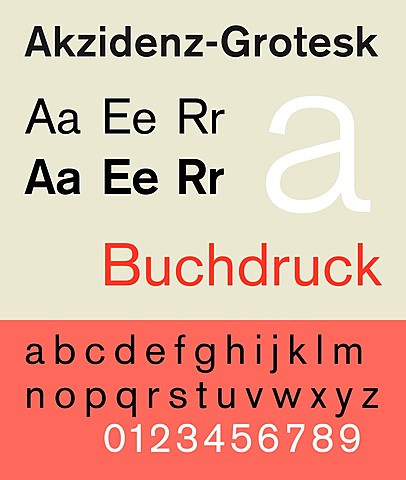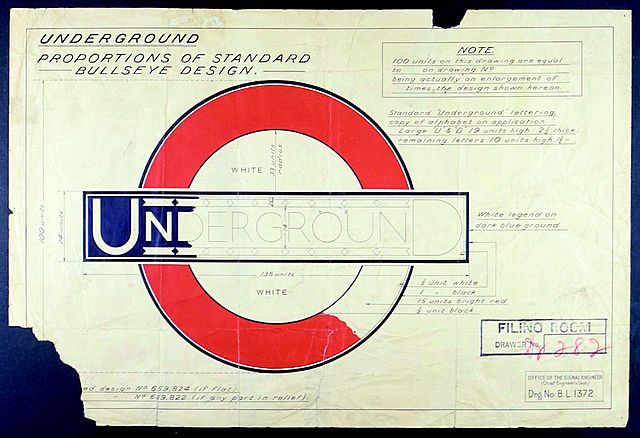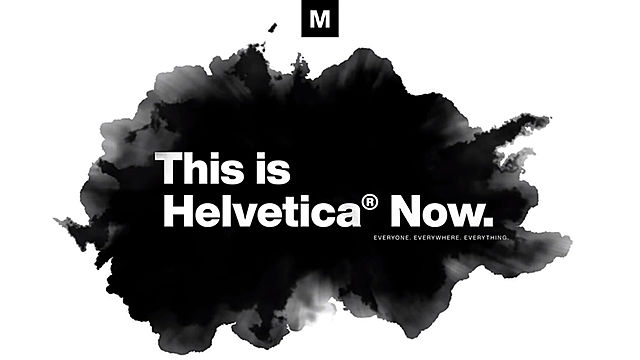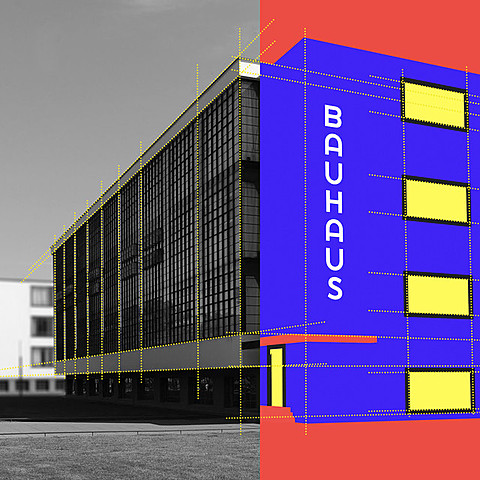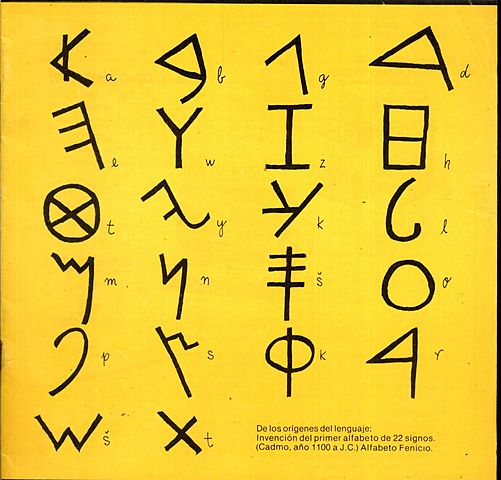
Por la zona de Siria. Se calcula que se implementaron estos lenguajes entre el 4000 a. C. y el 100 a.C.
Fenicio: 22 simbolos que representan sonidos. Creación de un protoalfabeto.
Arameo: Creación del árabe y hebreo
Griego: Singos de puntuación, escritura de izquierda a derecha, vocales y espacios entre palabras
Romano: Alfabeto propio de 26 letras y 7 de ellas se utilizan como números. -
Creación de mayusculas y minisculas carolingias, siendo la base de la tipografía moderna. Creación de los números además de 52 letras, simbolos y signos de puntuación.
Por Gutemberg
A partir de ahora se crean libros más rápido y se originan las primeras tipografías Oldstyle. -
Nuevas fuentes de letra, creación de la negrita y nuevos remates.
Dió lugar al arte comercial y se crean carteles de vanguardía.
Creación de letreros del metro de Londres, icono de la vida metropolitana. Cambio de 2 épocas
Creación del tipo de letra "Futura"
Creación del tipo de letra Helvetica, con 34 grosores diferentes
Movimiento Hippie influencia del Art Noveau
Utilización de los ordenadores.
Movimiento Punk. -
Macintosh revoluciona el mundo de los ordenadores, con lo cual la producción de letras está bajo el control de los diseñadores.
Experimentación con la tipografía.
La tipografía como mensaje -
Infinitas posibilidades para los diseñadores
Un gran pluralismo